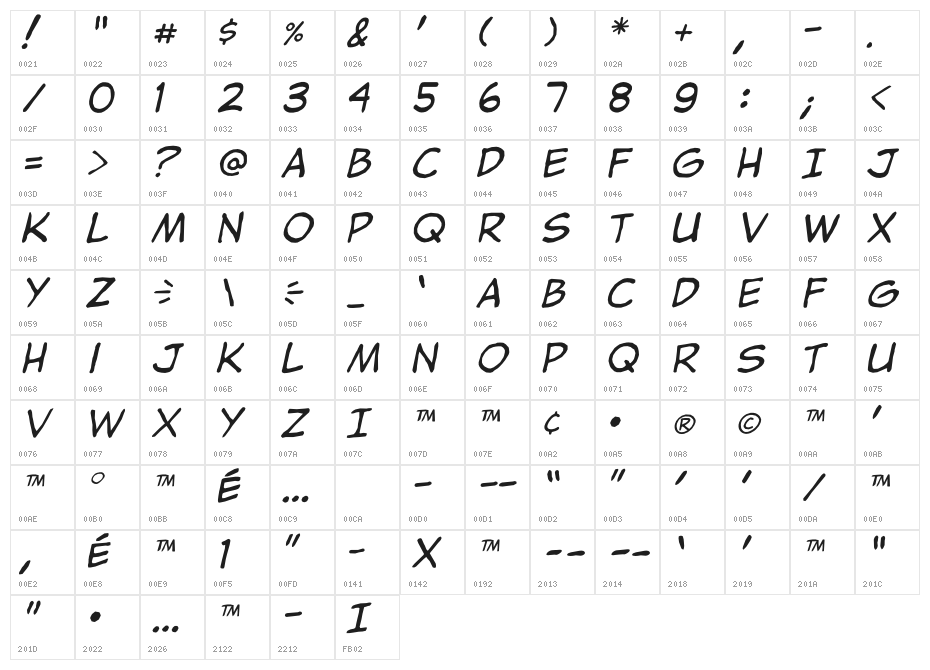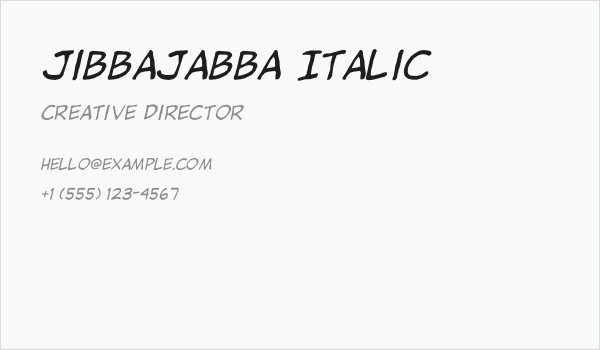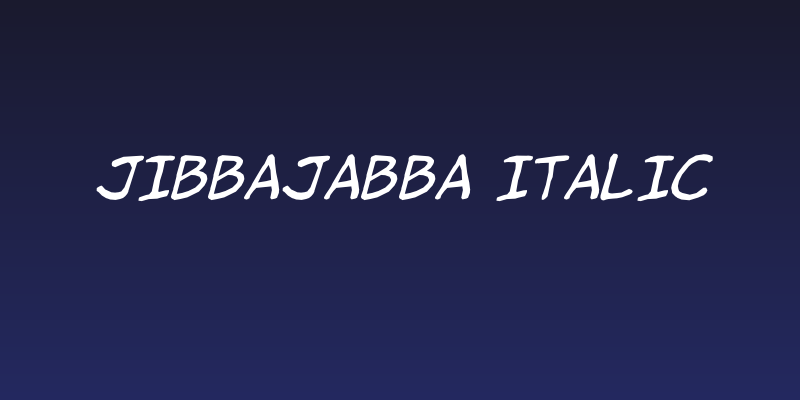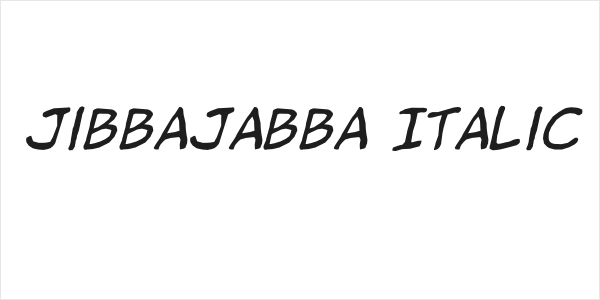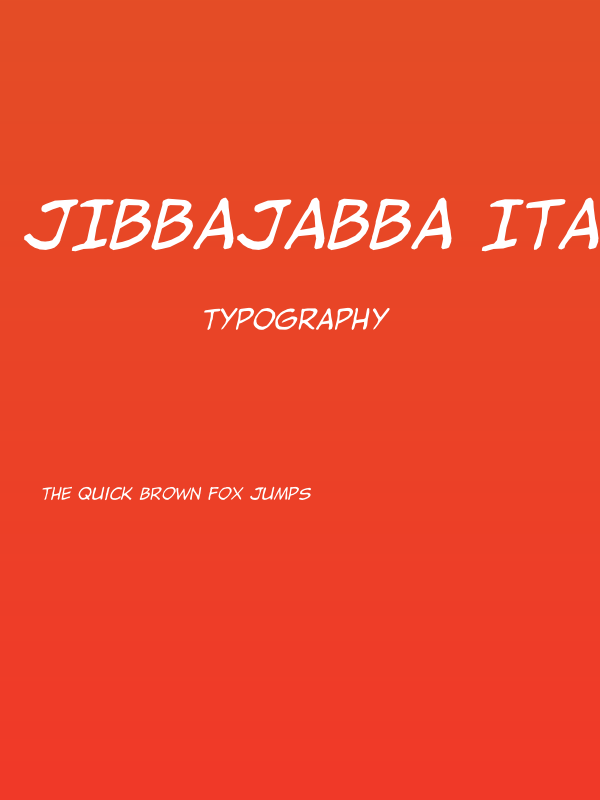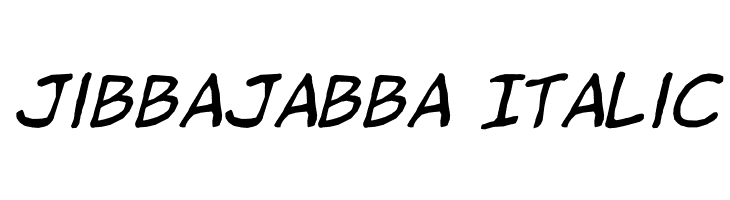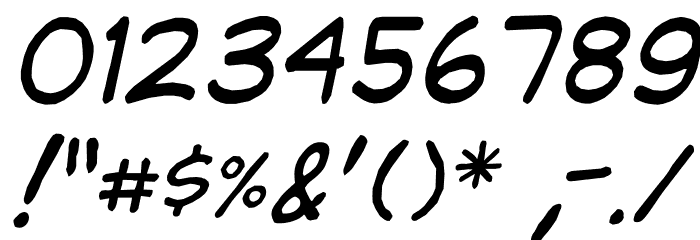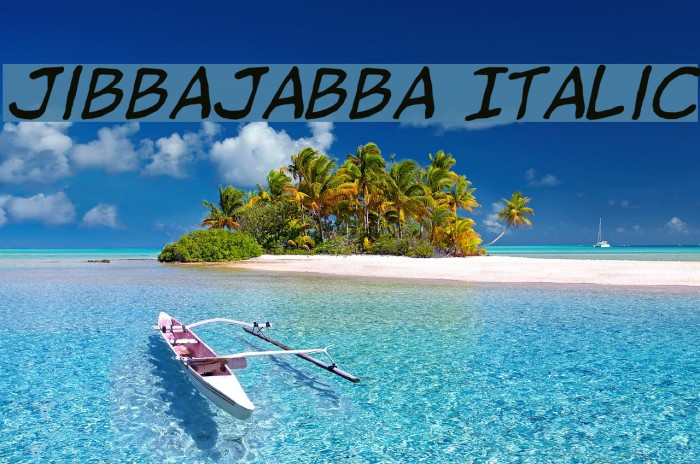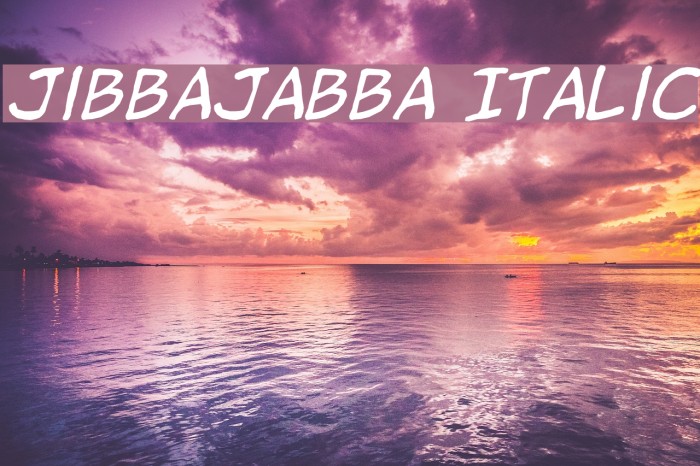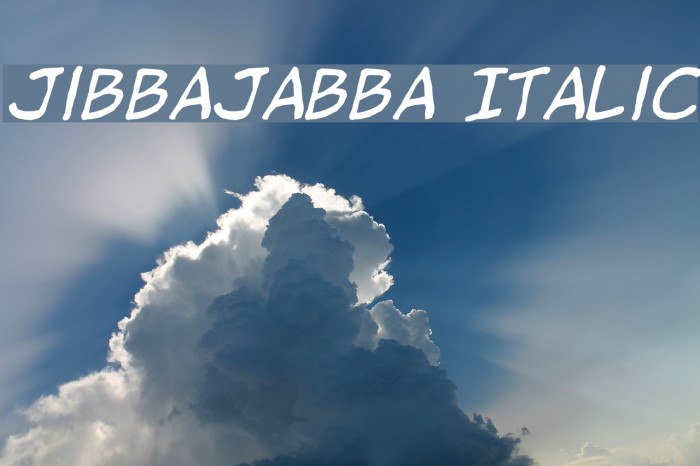
jibbajabba Italic Font
| Stile generale | Casual, Dynamic |
| Caso d'uso | Headlines, Logos, Informal Invitations |
| Progetti proposti | Ideal for projects that require a personal touch, such as greeting cards, invitations, or playful branding materials. It can also be used in digital content that aims to engage a youthful audience. |